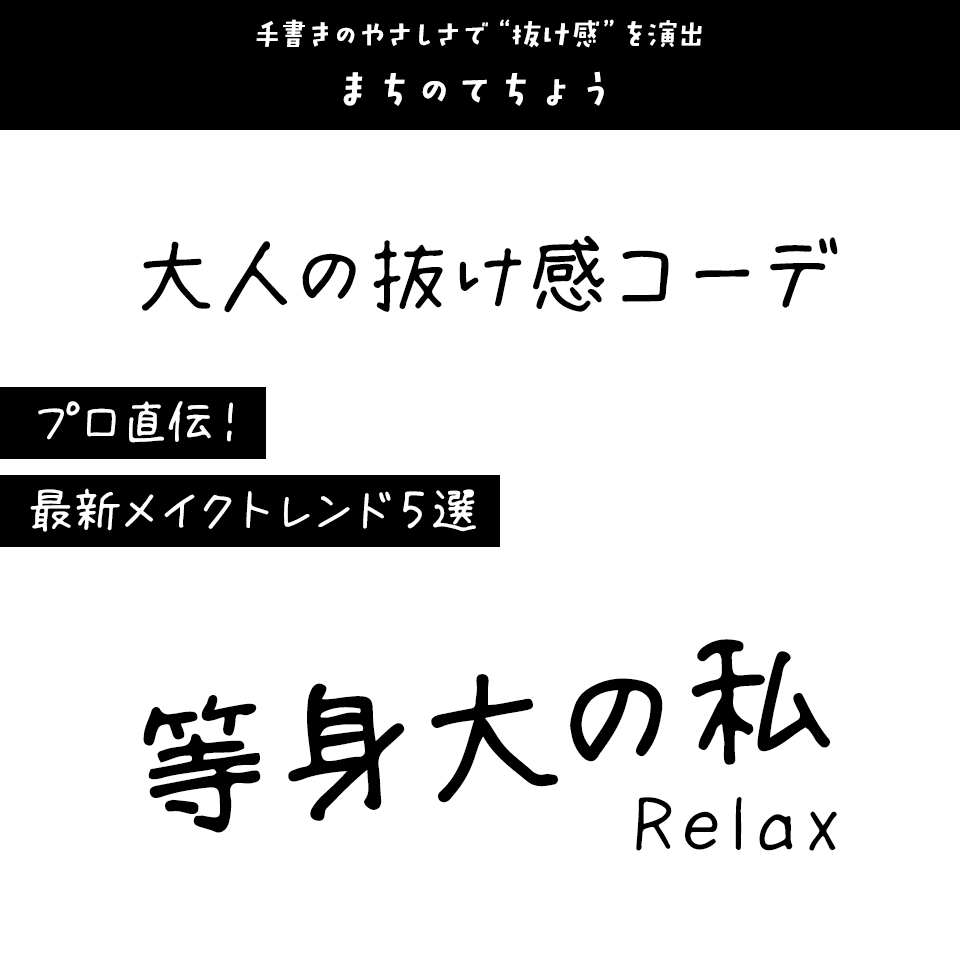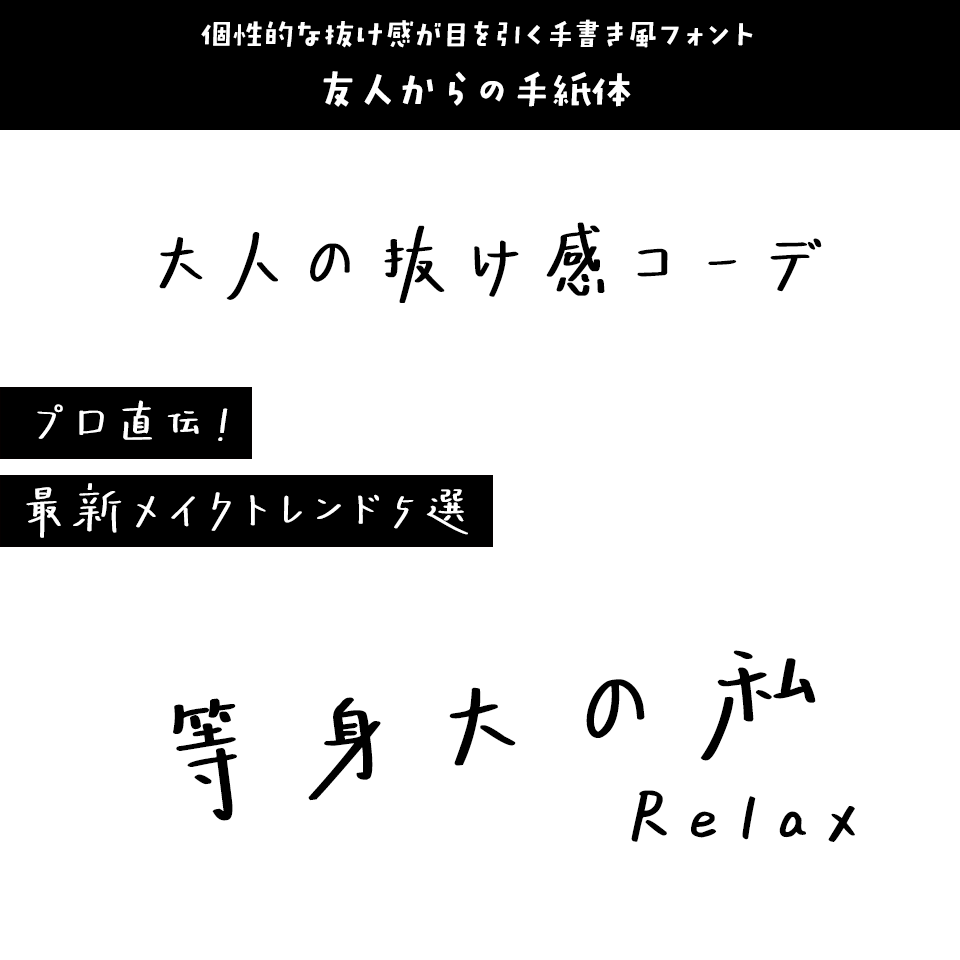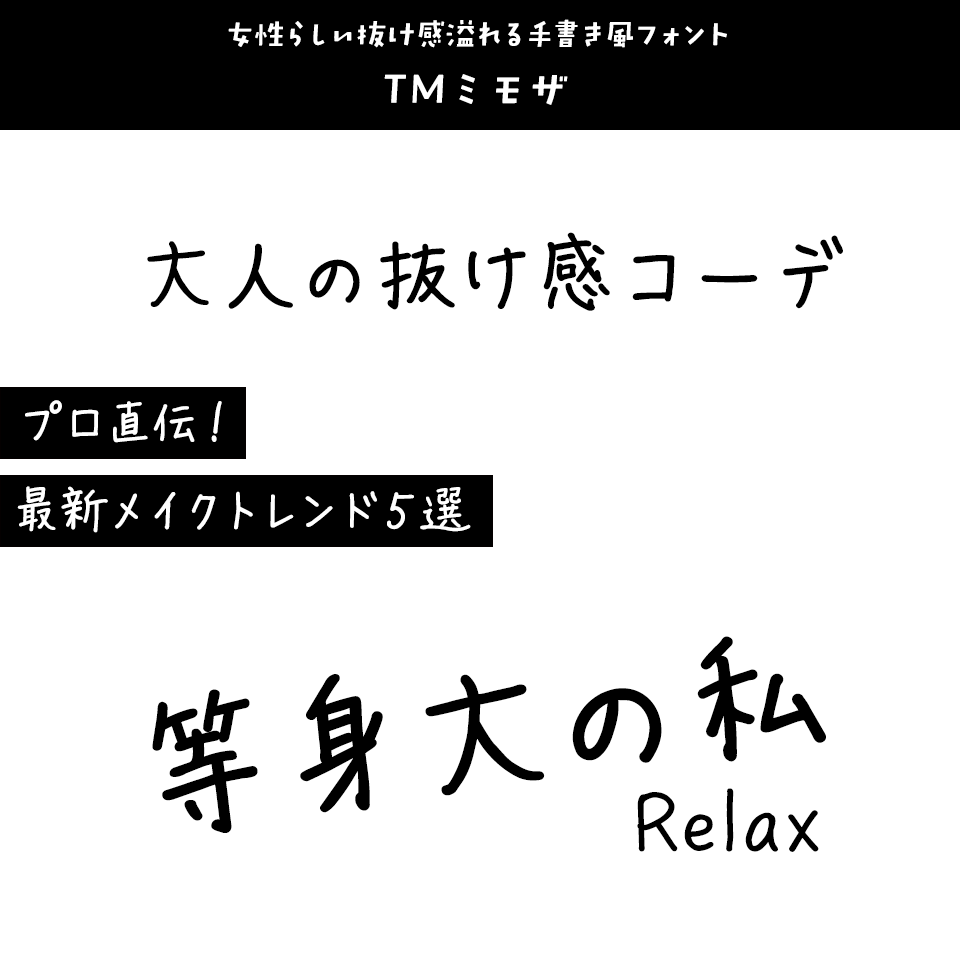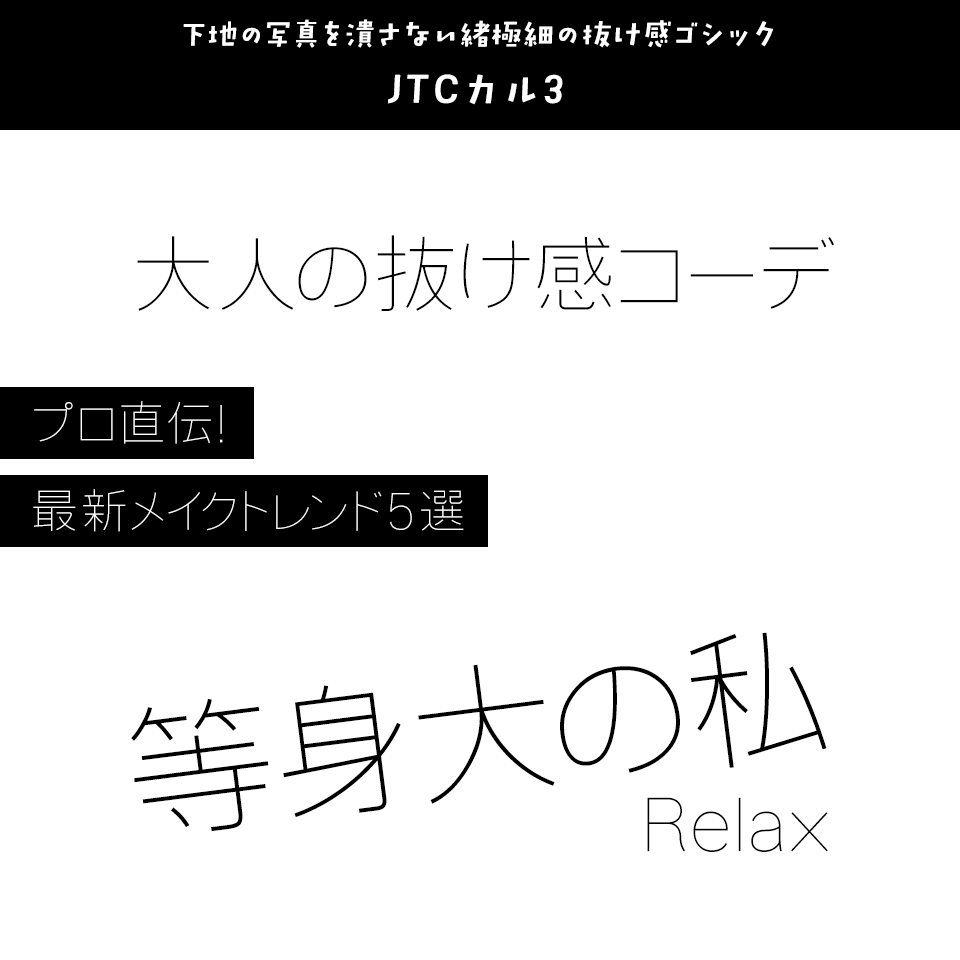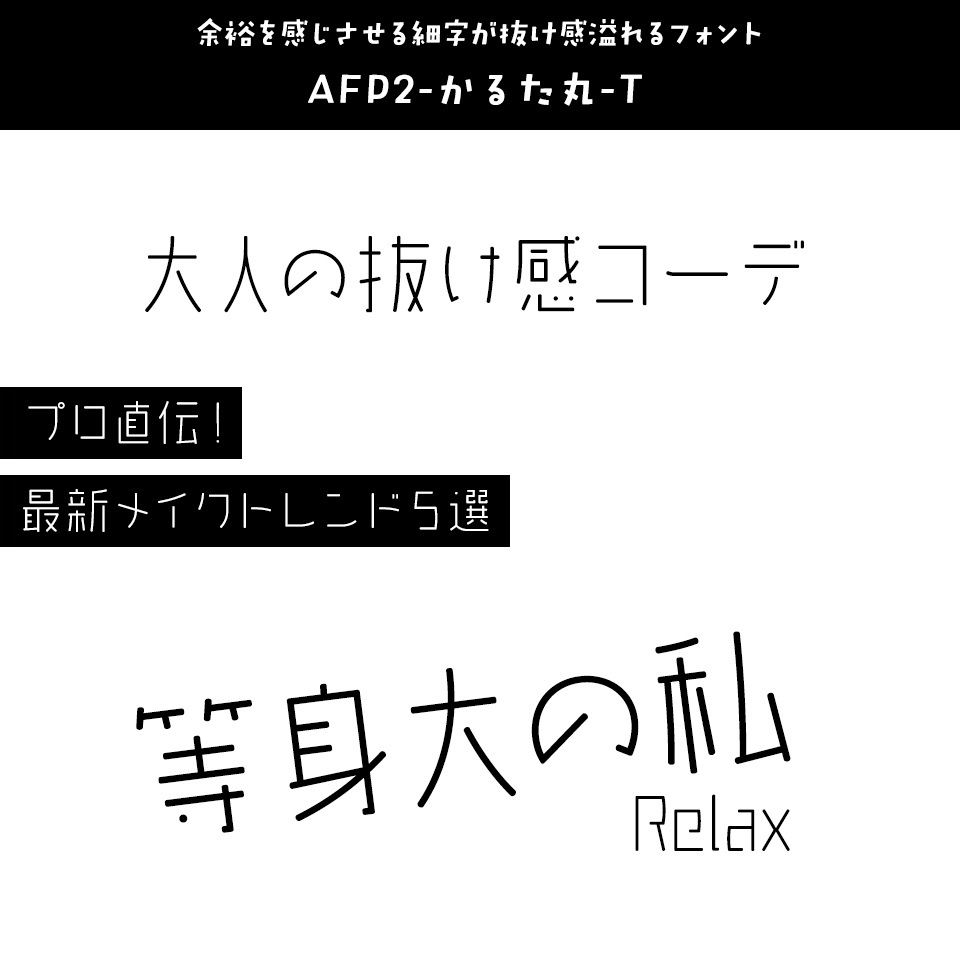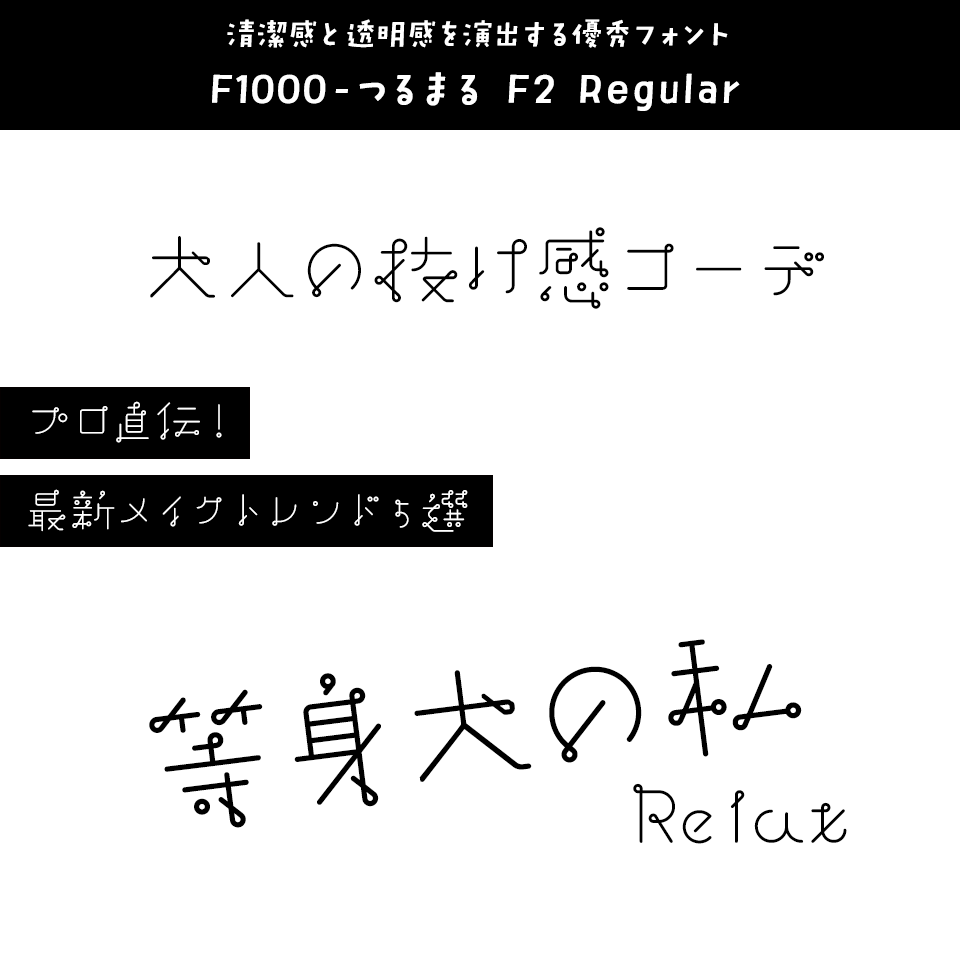
今回は「インスタに合う抜け感」があるフォント。日々フォントのことばかり考えている当店スタッフが直感的に選んだフォントをご紹介します。
「インスタに合う抜け感」があるフォントをスタッフが選びました
「インスタに合う抜け感」があるフォント まちのてちょう
手書きのやさしさで“抜け感”を演出
まちのてちょう【まち@machicooooo】
「インスタに合う抜け感」があるフォント まちのてちょう
iPadとApple Pencilで丁寧に描かれた手書きフォント。長文でも読みやすく、SNS画像や創作活動にぴったり。選ぶだけで自然な抜け感が生まれます。
「インスタに合う抜け感」があるフォント 左利きの彼女
細くて繊細なタッチで、やさしい抜け感
左利きの彼女【Hitomi Shibuya】
「インスタに合う抜け感」があるフォント 左利きの彼女
左利きの作者が一文字ずつ丁寧に書き上げた、細くやさしい手書きフォント。揺らぎや表情に抜け感が宿り、SNS画像や創作物にナチュラルな空気感を添えてくれます。
「インスタに合う抜け感」があるフォント 心描き体
ペンで書いたような趣を感じるフォント
心描き体【楽フォント】
「インスタに合う抜け感」があるフォント 心描き体
意図的に引き延ばした点画が、力強さとリズム感を演出します。広告、タイトル、説明文、映画字幕など、多様なデザイン用途に適しています。
「インスタに合う抜け感」があるフォント アングル
リアルな手書きのリズムが抜け感を生み出すフォント
アングル【toktaro fonts】
「インスタに合う抜け感」があるフォント アングル
手書き文字のような大小のリズムある文字を作れる、バリアブル(可変)フォントです。
「インスタに合う抜け感」があるフォント 空とひこうき
インクのにじみやラフな抜け感が特徴
空とひこうき【鈴木メモ】
「インスタに合う抜け感」があるフォント 空とひこうき
「空とひこうき」は、空に長く伸びて行くひこうき雲をイメージした書体。フチのにじみや先端のインク溜まり、勢いのある線の強弱などを生かしたリアル感のある手書き文字です。
「インスタに合う抜け感」があるフォント 桜と少女体
手書きの抜け感が欲しい方におすすめ
桜と少女体【楽フォント】
「インスタに合う抜け感」があるフォント 桜と少女体
ゆったりした気分で、つるつるした紙に細い平筆で描かれた書体。メリハリがあり、字が右上に傾いてすっきりとしています。息をしている間に自由な感覚が生まれてくるような視覚表現力があります。
「インスタに合う抜け感」があるフォント 友人からの手紙体
個性的な抜け感が目を引く手書き風フォント
友人からの手紙体【楽フォント】
「インスタに合う抜け感」があるフォント 友人からの手紙体
筆画を下向きに引き伸ばしたエレメントが特徴的な、シックで自由な感覚の手書きフォント。
「インスタに合う抜け感」があるフォント TMミモザ
女性らしい抜け感溢れる手書き風フォント
TMミモザ【タンデムフォント】
「インスタに合う抜け感」があるフォント TMミモザ
ペンのにじみを残した、自然で穏やかな女性の手書き書体。特典収録の装飾素材も抜け感の演出にかなり使えます!
「インスタに合う抜け感」があるフォント 波とかもめ
柔らかく脱力したような手書きフォント
波とかもめ【鈴木メモ】
「インスタに合う抜け感」があるフォント 波とかもめ
丸いマーカーでノートに書いたような、気取らない普段使いの手書きフォントです。ふっくらとした曲線のカーブと、少し太めの線で柔らかい印象に。 弾むような伸び上がりや、脱力したような払いを入れて、リラックスした雰囲気を持った太め・丸め・ユーモアのある手書きフォントが"ちょうどいい"抜け感を演出します。
「インスタに合う抜け感」があるフォント 手書き屋本舗 TAまさあき
右肩上がりと四角いフォルムが個性的
手書き屋本舗 TAまさあき【スキルインフォメーションズ】
「インスタに合う抜け感」があるフォント 手書き屋本舗 TAまさあき
右肩上がりの四角いフォルムが個性的な手書きフォント。細いラインが抜け感を演出します。
「インスタに合う抜け感」があるフォント iroha 23kaede
強すぎず、ゆるすぎない自然な抜け感
iroha 23kaede【砧書体制作所】
「インスタに合う抜け感」があるフォント iroha 23kaede
漢字は線の均一化を図り、モダンにしました。強さをだすために直線を意識し、安心感をだすためにふところを広くしています。先端部をあえて直角処理にしているため、漢字だけを組むとロゴタイプのような見え方をします。
「インスタに合う抜け感」があるフォント DSサラ
すっきり、あっさり味のナチュラルな書体。
DSサラ【七種泰史/デザインシグナル】
「インスタに合う抜け感」があるフォント DSサラ
細身のウェイトで小さい文字でも読みやすく、ナチュラルデザインにぴったりです。
「インスタに合う抜け感」があるフォント F1000-ベイビーウォーク F2 Regular
ナチュラルで優しい印象を与える手書き風フォント
F1000-ベイビーウォーク F2 Regular Regular【FONT1000】
「インスタに合う抜け感」があるフォント F1000-ベイビーウォーク F2 Regular
空間を感じさせる抜け感のある文字、適度な丸みで優しさを演出するナチュラルなフォント、ほっこり可愛らしいフォルムが特徴です。
「インスタに合う抜け感」があるフォント JTCカル3
下地の写真を潰さない緒極細の抜け感ゴシック
JTCカル3【ニィスフォント】
「インスタに合う抜け感」があるフォント JTCカル3
超極細フォントのファミリーです。写真や図案の上に載せても下地を踏み潰さないインスタにぴったりのゴシック体フォントです。
「インスタに合う抜け感」があるフォント 筆技名人フォント モトヤアネモネ1
程よく力の抜けた美しいデザイン
モトヤアネモネ1【モトヤ】
「インスタに合う抜け感」があるフォント モトヤアネモネ1
淡々しさと儚さを表現し、今にも消えてしまいそうな淡いイメージを持たせています。文面に応じて悲しげで切ない感情を表現することができます。
「インスタに合う抜け感」があるフォント 書房体
スマートで洗練された美しさが抜け感を生み出すフォント
書房体【楽フォント】
「インスタに合う抜け感」があるフォント 書房体
古代書体の優雅さや高級感を感じさせるやや細めな長方形の字面を基盤に、重心を高く持ち、美しく洗練されたスマートな線で現代的でシャープかつモダンな印象を与えます。線の両端は柔らかく角を取り、一部のエレメントをシンプルに仕上げ、奥行きのあるデザインを実現しました。
「インスタに合う抜け感」があるフォント AFP2-かるた丸-T
余裕を感じさせる細字が抜け感溢れるフォント
AFP2-かるた丸-T【FONT1000】
「インスタに合う抜け感」があるフォント AFP2-かるた丸-T
エレメントは直線的で先端を丸くした丸文字。硬めのデザインですが余裕を感じさせる細字です。ちょっと和風でキュートな書体、軽やかな文字組をお楽しみください。
「インスタに合う抜け感」があるフォント 丸明オールド
大人な抜け感にふさわしいフォント
丸明オールド【砧書体制作所】
「インスタに合う抜け感」があるフォント 丸明オールド
明朝体にも丸明朝体というカテゴリーがあることを実証した書体。直線を意識した漢字、筆の動きを強調したカナ、四角いスペースにこだわらない形。
「インスタに合う抜け感」があるフォント F1000-つるまる F2 Regular